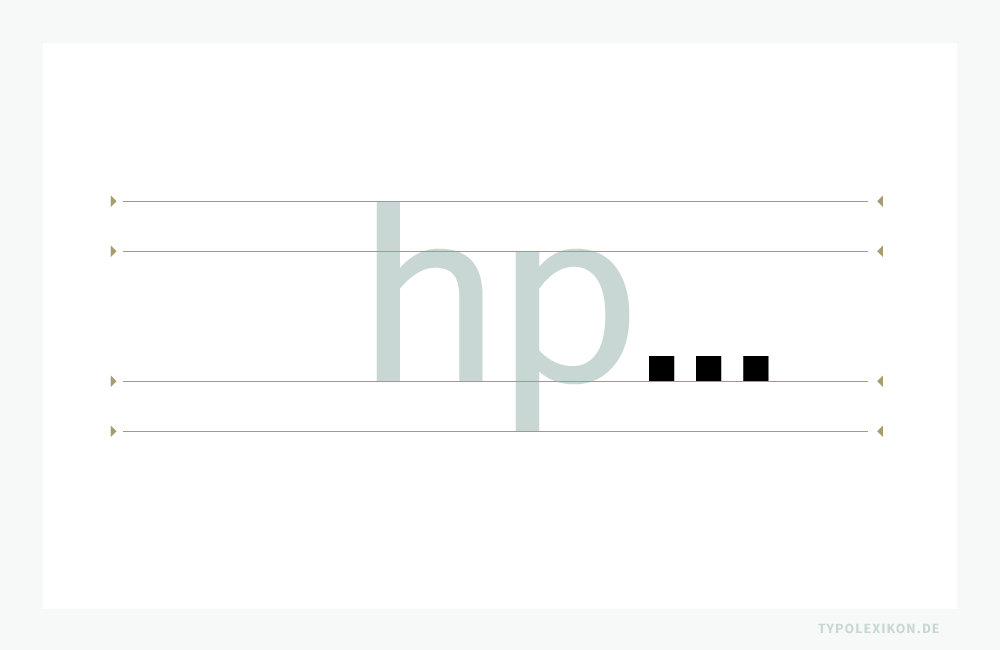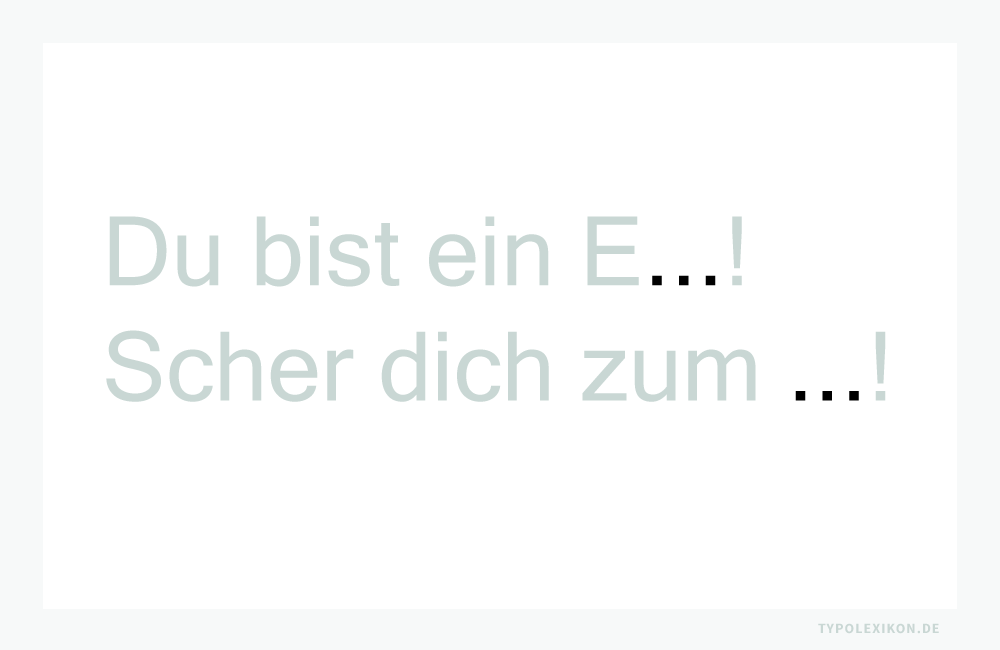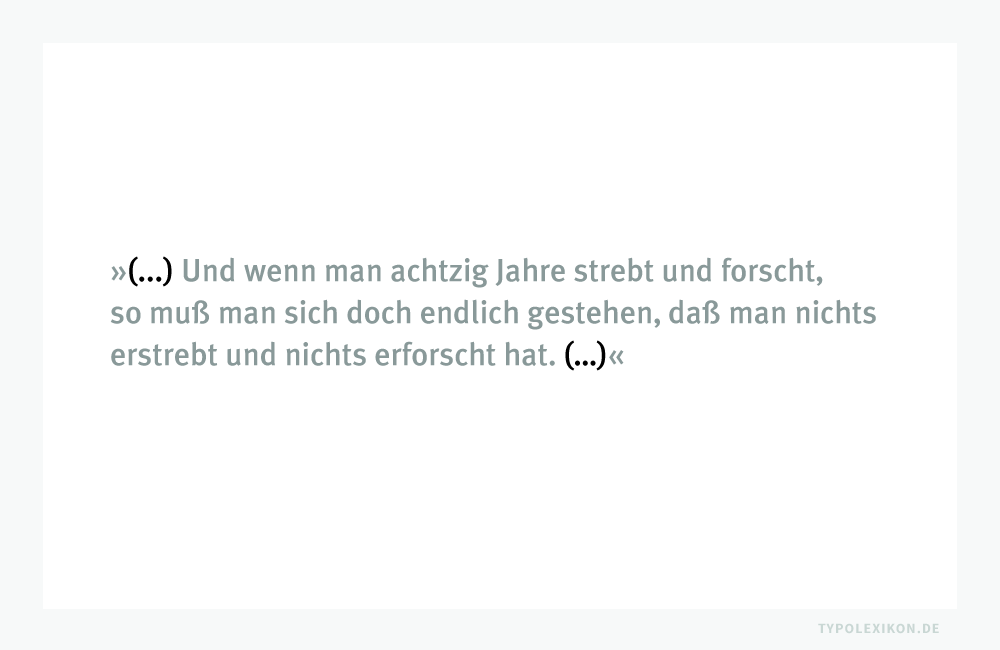
Auslassungspunkte
Auslassungspunkte sind orthographische Satzzeichen bzw. Interpunktionszeichen. Sie werden als Auslassungszeichen, Fortsetzungspunkte, mathematischen Operatoren und als wertersetzende Zeichen verwendet. In der Typografie zählen Auslassungspunkte zu den Ellipsenzeichen, die zu den Sonderzeichen gehören. Auch als »Dreipunkt« bezeichnet.
Der Dreipunkt (Auslassungspunkte) ist ein horizontales Ellipsenzeichen auf der Grundlinie einer Schrift. Auslassungspunkte dienen als Auslassungszeichen für Ellipsen, als Fortsetzungspunkte, als mathematischen Operatoren und als wertersetzende Zeichen. Beispiel gesetzt in der »Microsoft Sans Serif«, einer Systemschrift von Microsoft®.
Auslassungspunkte stehen für eine Textauslassung (Ellipse) 1)  oder eine Gesprächs- bzw. Gedankenpause, die durch drei aufeinanderfolgende Punkte mit und ohne Leerraumzeichen gekennzeichnet wird. Bei der Auslassung in einem Wort wird kein Leerraumzeichen gesetzt (z.B. Du bist ein E…!), bei einer Auslassung eines Satzteils wird mit Leerraumzeichen gegliedert (z.B. Scher dich zum …!).
Auslassungspunkte stehen für eine Textauslassung oder eine Gesprächs- bzw. Gedankenpause. Bei der Auslassung in einem Wort wird kein Leerraumzeichen gesetzt (z.B. Du bist ein E...!), bei einer Auslassung eines Satzteils (Ellipse) wird mit Leeraumzeichen gegliedert (z.B. Scher dich zum ...!).
Auslassungspunkte stehen für eine Textauslassung oder eine Gesprächs- bzw. Gedankenpause. Bei der Auslassung in einem Wort wird kein Leerraumzeichen gesetzt (z.B. Du bist ein E…!), bei einer Auslassung eines Satzteils (Ellipse) wird mit Leeraumzeichen gegliedert (z.B. Scher dich zum …!).
Die Auslassungspunkte werden mit Parenthesen (Klammern) flankiert, wenn ein oder mehrere Teile eines wörtlichen Zitats ausgelassen wurden, also die zitierte Quelle verkürzt wurde. Beispiel: Teil eines Zitats von Alexander von Humboldt (1769–1859).
Auslassungspunkte werden mit Parenthesen (Klammern) flankiert, wenn die Auslassung innerhalb eines wortgetreuen (direkten) Zitats in Anführungszeichen erfolgt bzw. wenn eine Passage nicht vollständig zitiert wird.
Auslassungspunkte werden auch als Fortsetzungspunkte im Sinne von »usw.« bzw. »etc.« verwendet, um Intervalle, Folgen oder Mehrfachverkettungen anschaulich darzustellen. In der Mathematik und im wissenschaftlichen Formelsatz zählen Auslassungspunkte auch zu den mathematischen Operatoren. Im klassischen Tabellensatz nach der DIN 55301 (zurückgezogen) 2)  ist der Dreipunkt ein wertersetzendes Zeichen für »Angabe fällt später an«. Die DIN 55301 wurde zurückgezogen und durch die DIN 5008:2020-03 »Schreib- und Gestaltungsregeln für die Text- und Informationsverarbeitung« 3) weitgehend ersetzt.
Auslassungspunkte entwickelten sich Ende des 18. Jahrhunderts sukzessive aus den bis dahin üblichen drei Auslassungssternen (z.B. Herr B*** aus B***). 4)
Orthographie (Deutsche Rechtschreibung)
Auslassungspunkte können sowohl am Anfang, im oder am Ende eines Wortes, eines Satzes oder einer Formel stehen. In der deutschen Orthographie (Rechtschreibung) wird die Verwendung der Auslassungspunkte durch das »Amtliche Regelwerk der deutschen Rechtschreibung« 5)  geregelt. Dort heißt es:
§ 54 | Das erste Wort eines Ganzsatzes schreibt man groß.
Auslassungspunkte (…) zu Beginn eines Ganzsatzes gelten als Satzanfang; entsprechend bleibt die Schreibung des folgenden Wortes unverändert. Dies gilt auch für Überschriften, Werktitel und dergleichen.
Beispiel:
… und gab keine Antwort.
§ 99 | Mit drei Punkten (Auslassungspunkten) zeigt man an, dass in einem Wort, Satz oder Text Teile ausgelassen worden sind.
Beispiele:
Du bist ein E…!
Scher dich zum …!
»… ihm nicht weitersagen«, hörte er ihn gerade noch sagen.
Der Horcher an der Wand …
Beispiel für einen vollständigen Text:
In einem Buch heißt es: »Die zahlreichen Übungen sind konkret auf das abgestellt, was vorher behandelt worden ist. Sie liefern in der Regel Material, mit dem selbst gearbeitet und an dem geprüft werden kann, ob das, was vorher dargestellt wurde, verstanden worden ist oder nicht. Die im Anhang zusammengestellten Lösungen machen eine unmittelbare Kontrolle der eigenen Lösungen möglich.«
Beispiel des Textes mit Auslassungen:
In einem Buch heißt es: »Die … Übungen … liefern … Material, mit dem selbst gearbeitet … werden kann … Die … Lösungen machen eine … Kontrolle … möglich.«
§ 100 | Stehen die Auslassungspunkte am Ende eines Ganzsatzes, so setzt man keinen Satzschlusspunkt.
Beispiele:
Ich habe die Nase voll und …
Diese Szene stammt doch aus dem Film »Die Wüste lebt« …
Mit »Es war einmal …« beginnen viele Märchen.
Viele Märchen beginnen mit den Worten: »Es war einmal …«
Aber: Verflixt! Ich habe die Nase voll und …!
Typografischer Schriftsatz
Auslassungspunkte können durch drei einzelne aufeinanderfolgende Punkte oder durch ein eigenständiges Satzzeichen in Form eines Dreipunkts dargestellt werden, welches als Zeichen im internationalen Standard von Unicode® ab Version 1.1.0 (Juni 1993) für Computerzeichensätze unter »Horizontal Ellipsis« (U+2026) geführt wird. 6)
PC-Tastaturbelegung Horizontal Ellipsis (U+2026):
Satzzeichen         #  Windows       macOS      Linux
Auslassungspunkte   …  [alt]+[0133]  [alt]+[.]  [alt gr]+[.]
HTML Code Horizontal Ellipsis (U+2026):
Satzzeichen         #   Hexadezimal  Dezimal  Signiert
Auslassungspunkte   …   …     …  …
Auslassungspunkte aus einzelnen Punkten können spationiert bzw. an die individuelle Laufweite einer Schrift angepasst werden.
Die Laufweite eines solitären Dreipunktzeichens (z.B. U+2026) hingegen ist fix. D.h., es besitzt eine durch den Schriftgestalter*in vorgegebene Laufweite und kann deshalb nur in der Normalschriftweite (NSW) verwendet werden. 7) Auslassungspunkte in Form eines einzelnen Satzzeichens besitzen in der Regel deutlich weniger Laufweite, als Auslassungspunkte, die aus drei einzelnen Punkten gesetzt werden, dies gilt insbesondere bei dicktengleichen Schriften. 8)  9)
Sind Auslassungspunkte mit runden (…), eckigen […] oder geschweiften Parenthesen {…} im Zuge der Nuancierung flankiert, werden im geschlossenen Schriftsatz keine Leerraumzeichen eingefügt. Im Feinsatz jedoch werden flankierte Auslassungspunkte leicht spationiert und immer auf die optische Laufweite der verwendeten Schrift abgestimmt. Im deutschen Schriftsatz sollte bei Antiquas der Zeichenabstand der einzelnen Punkte in der NSW mindestens 1/4 Geviert (ca. ein halbes Leerraumzeichen) zu den Klammern betragen.10) Bei HTML-Texten (z.B. auf Websites oder in E-Mails) ist dies – ohne spürbaren Mehraufwand bei der Gestaltung und Anwendung eines CSS 11) – nicht oder kaum möglich.
↑1 Anmerkung: »Ellipse« wird auch als Synonym für »Auslassung« verwendet. In der Sprachwissenschaft bezeichnet man mit Ellipse das Fehlen von syntaktisch notwendigen Satzteilen. In der Rhetorik ist die Ellipse ein Stilmittel, einen Satz grammatikalisch nicht vollständig und somit verkürzt zu formulieren. Teile eines Satzes werden ausgelassen, um eine Verstärkung zu bewirken, wobei der Inhalt klar zu verstehen ist. Auslassungspunkte sind somit sinnentsprechend keine Ellipsen sondern Ellipsenzeichen (Auslassungszeichen).
↑2 Anmerkung: Die DIN 55301 ist eine Norm für die »Gestaltung statistischer Tabellen«, die 1978 durch das Deutsche Institut für Normung e.V. (DIN) erarbeitet wurde. Weiterführende Informationen online unter https://www.beuth.de/de/norm/din-55301/782608 (27.3.2023).
↑3 Anmerkung: Weiterführende Informationen online unter https://www.beuth.de/de/norm/din-5008/318422674 (27.3.2023).
↑4 Quelle: Tschichold, Jan: Ausgewählte Aufsätze über Fragen der Gestalt des Buches und der Typografie, Seite 150, Birkhäuser Verlag Basel, 1975, ISBN 3-7643-1946-1.
↑5 Quelle: Deutsche Rechtschreibung, Regeln und Wörterverzeichnis, entsprechend den Empfehlungen des Rats für deutsche Rechtschreibung, überarbeitete Fassung des amtlichen Regelwerks 2016. Online verfügbar als PDF unter www.rechtschreibrat.com/DOX/rfdr_Regeln_2016_redigiert_2018.pdf (27.3.2023).
↑6 Anmerkung: Unicode® ist ein internationaler Standard des Unicode Consortiums, in dem langfristig für jedes Sinn tragende Schriftzeichen oder Textelement aller bekannten Schriftkulturen und Zeichensysteme ein digitaler Code festgelegt wird. Online verfügbar unter https://home.unicode.org (27.3.2023).
↑7 Tipp: Damit ein ausgeschlossenes Satzbild ohne optische Löcher entsteht, sollten Auslassungspunkte immer auf die Laufweite der verwendeten Schrift angepaßt sein, insbesondere wenn sie durch Parenthesen Flankiert werden.
↑8 Literaturempfehlung: De Jong, Ralf und Friedrich Forssman: Detailtypografie, Verlag Hermann Schmidt, Mainz, ISBN 978-3-87439-642-4.
↑9 Anmerkung: Autokorrektur-Optionen von Software, beispielsweise in Microsoft Word® oder WordPress®, können ggf. drei einzelne Punkte automatisch durch Auslassungspunkte (U+2026) ersetzen, was zu Irritationen führen kann. Des Weiteren können Probleme bei der automatischen Rechtschreibkorrektur auftreten.
↑10 Tipp: Werden Auslassungspunkte nicht in der Normalschriftweite verwendet, z.B. bei spationierten Headlines oder spationierten kursiven Textpassagen, sollten im Feinsatz immer nur Einzelpunkte verwendet werden, ansonsten ist eine Spationierung bzw. Anpassung an die Laufweite nicht möglich.